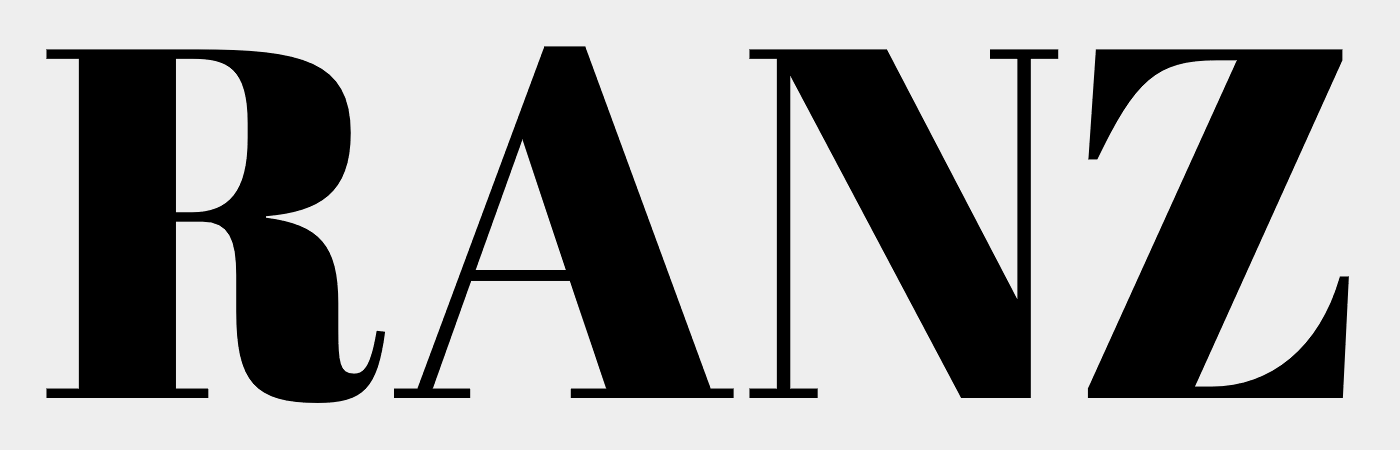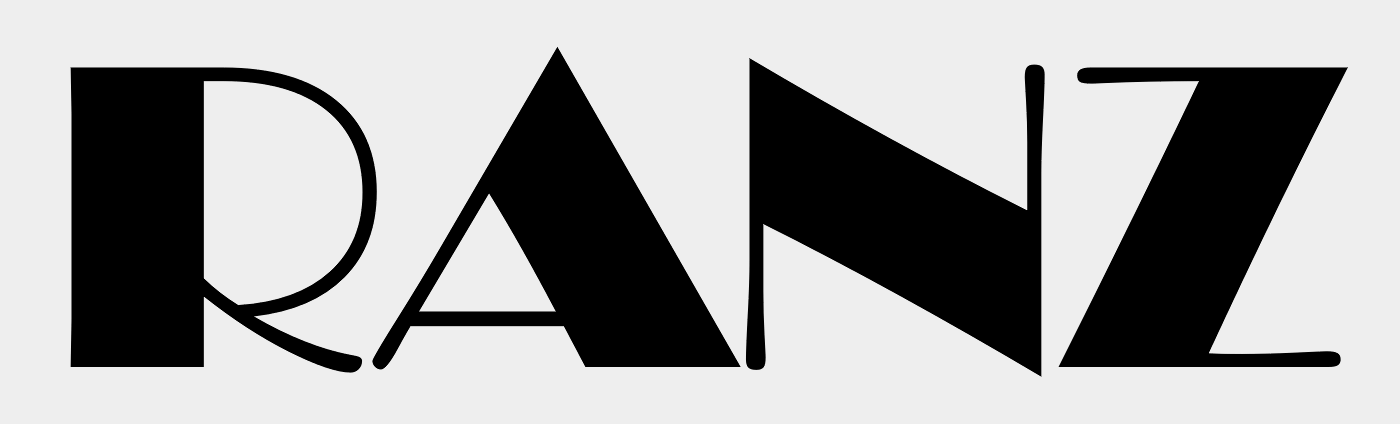
Moin, ich bin auf der Suche nach dieser oder einer ähnlichen Schrift.
Hängt seit ca. 70 Jahren über der Ladentür, habe leider kein anderes Foto.
Ich bin auch der Meinung diese oder was ähnliches, in den siebzigern noch im Kasten gehabt zu haben.
Wenn Du nur die vier Zeichen benötigst, finden sich hier im Forum auch viele versierte Kollegen, die Dir die Zeichen für ein kleines Salär perfekt nachbauen können. Frag bei Bedarf doch einfach mal in die Runde.
Danke für die Infos! Aber ich brauche völlig andere Zeichen und da habe ich keine Vorlage für. Wichtig ist der Charakter mit den extrem fetten und extrem dünnen Linien.
Wenn dir nur der große Kontrast zwischen den dünnen und fetten Linien wichtig ist, könnte dich vielleicht auch die kostenlose Abril Fatface interessieren. Die entspricht zwar nicht der von dir gesuchten Schrift, bietet jedoch den Kontrast zwischen den dünnen und den fetten Linien.
Vielleicht bist du ja schon mit der Broadway glücklich: